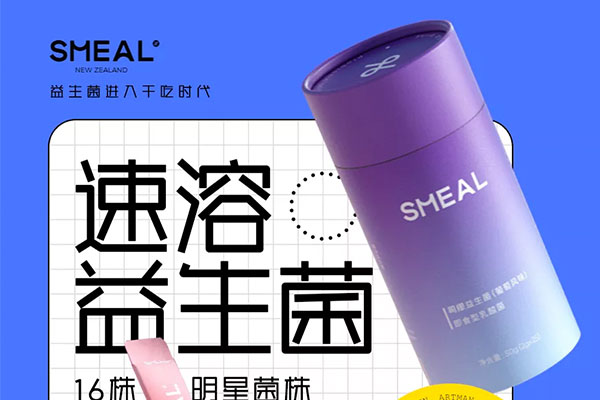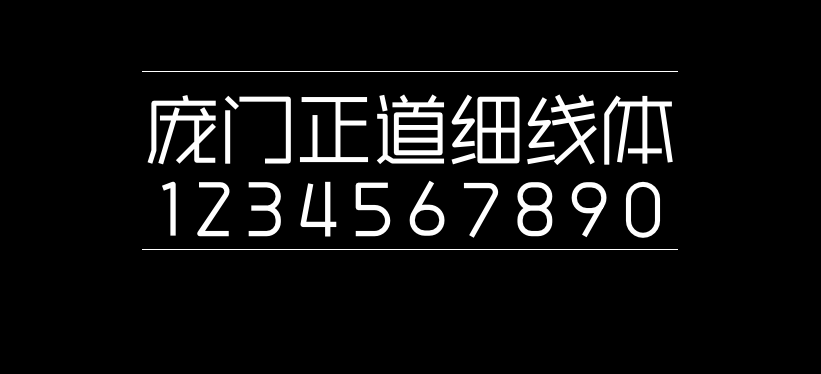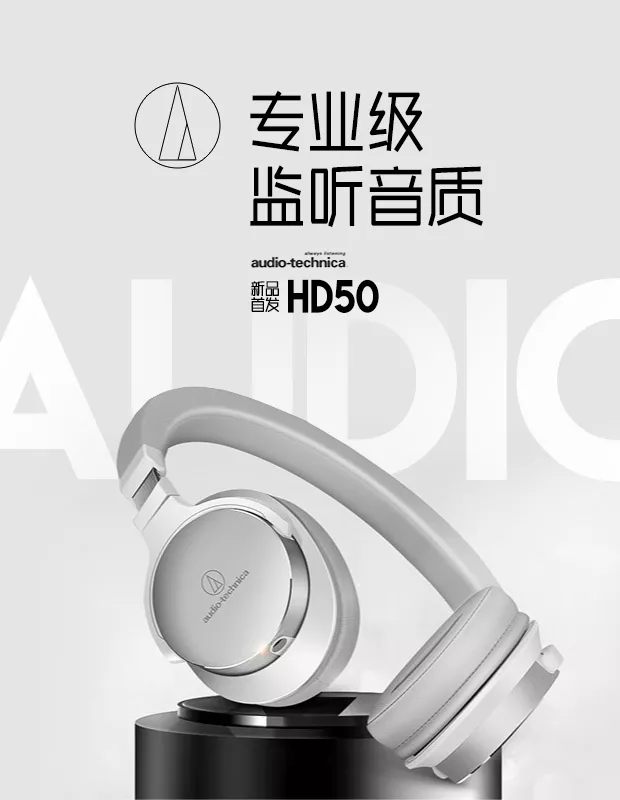
庞门正道细线体
庞门正道细线体是知名设计大V庞门正道联合胡晓波设计工作室推出的一款免费商用字体。
庞门正道细线体
以下是作者对该字体的介绍:
庞门正道的第八个年头,迈过今晚,就是第9年。
人生有多少个8年?我不知道。
我还能不能坚持写到下一个8年?我也不知道。
但是我知道一个8年,可以做很多有意义的事情。
就如2019年,我就和胡晓波工作室达成了合作,开发一款全新的字体,虽然我的计划是免费商用,但是胡晓波工作室是养着二三十设计师的商业机构,不可能说让他免费给我做,所以这次是按照他的商业报价后的友情折扣给我制作。多少钱就不说了,目前的商业品牌字库是30万一款,我花了同样不止十万就是了。
2020年其实已经交付,但是那时候我爸的那款字体也在同期制作,无暇接应那么多,所以这一款就安排在2021年的12月24日,8周年的时间发布。
这很可能是我发布的最后一款字体了。
为什么可能是最后一款?
没钱我失望了吗?并没有,因为我没有拿它赚钱的预期,没有希望,就没有失望,反而这种百万人使用之庞门正道系列字体的成就感带来的开心,可能我在其它地方花数十万并不能买得到。
今晚,让我再开心多一次。也让大家开心多一次。
全新庞门正道系列字体
庞门正道细线条,登场!
庞门正道细线体